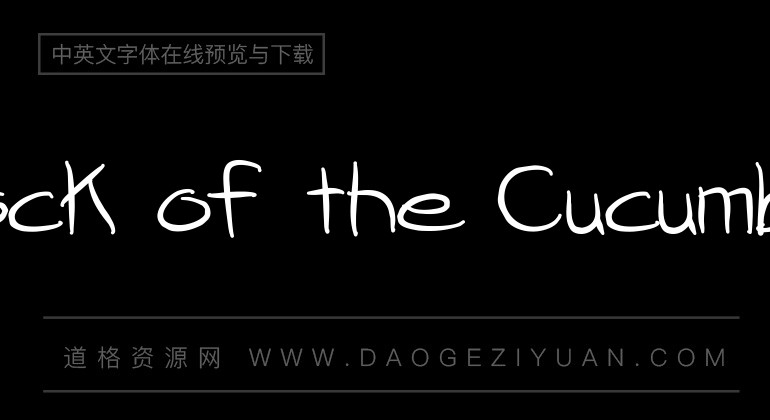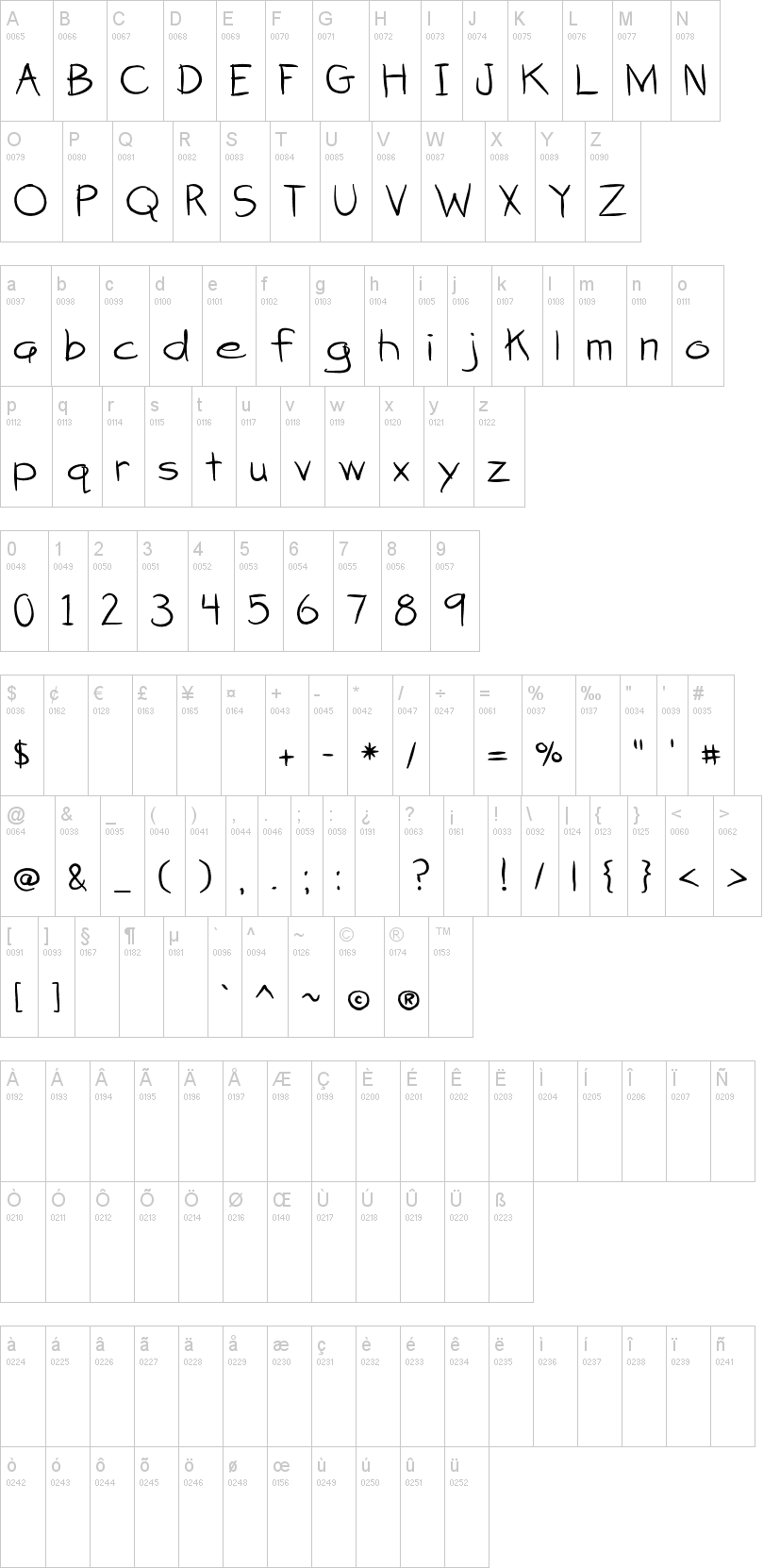
Attack of the Cucumbers
Attack of the Cucumbers 是一款漂亮的手写字体,由荷兰设计师Marije van Lidth de Jeude创作。它灵感来自蔬菜,以其细节丰富的设计,清晰的线条和现代的创意设计而闻名。它可以用于多种应用,如网页设计,平面设计,印刷和海报设计等。它有一种柔和的质感,使其成为一种优雅而又有趣的字体。
Attack of the Cucumbers是一款非常不错的手写艺术字体,具有很好的视觉感,适合于文化类的宣传设计、商业类品牌的广告和产品包装设计以及个性化文字排版等较多场景。